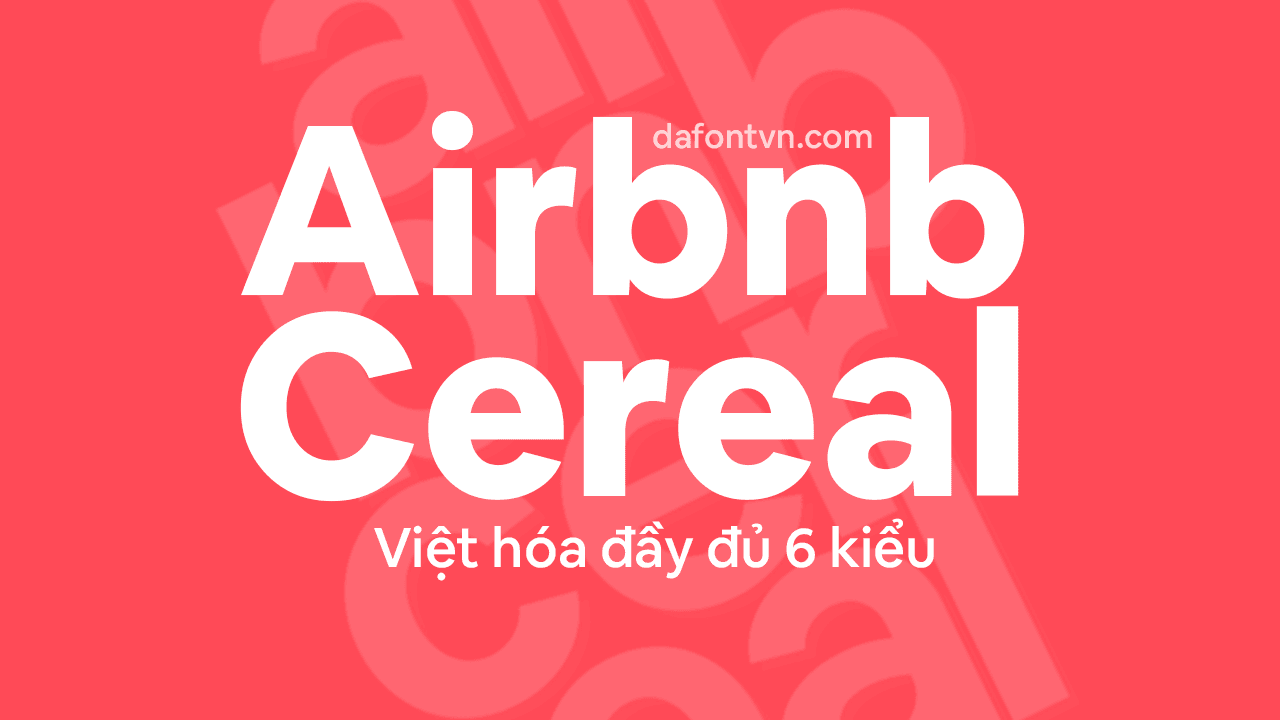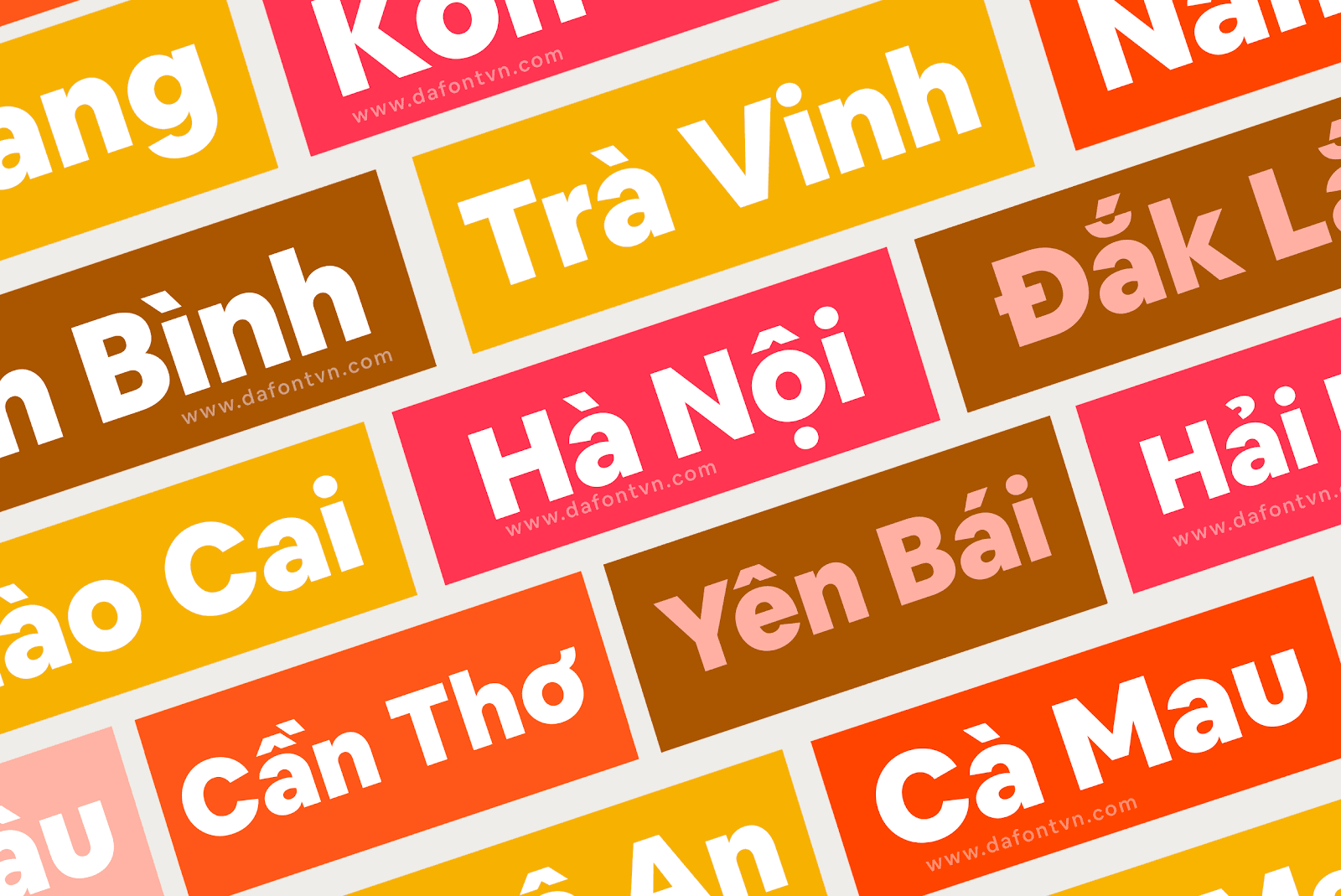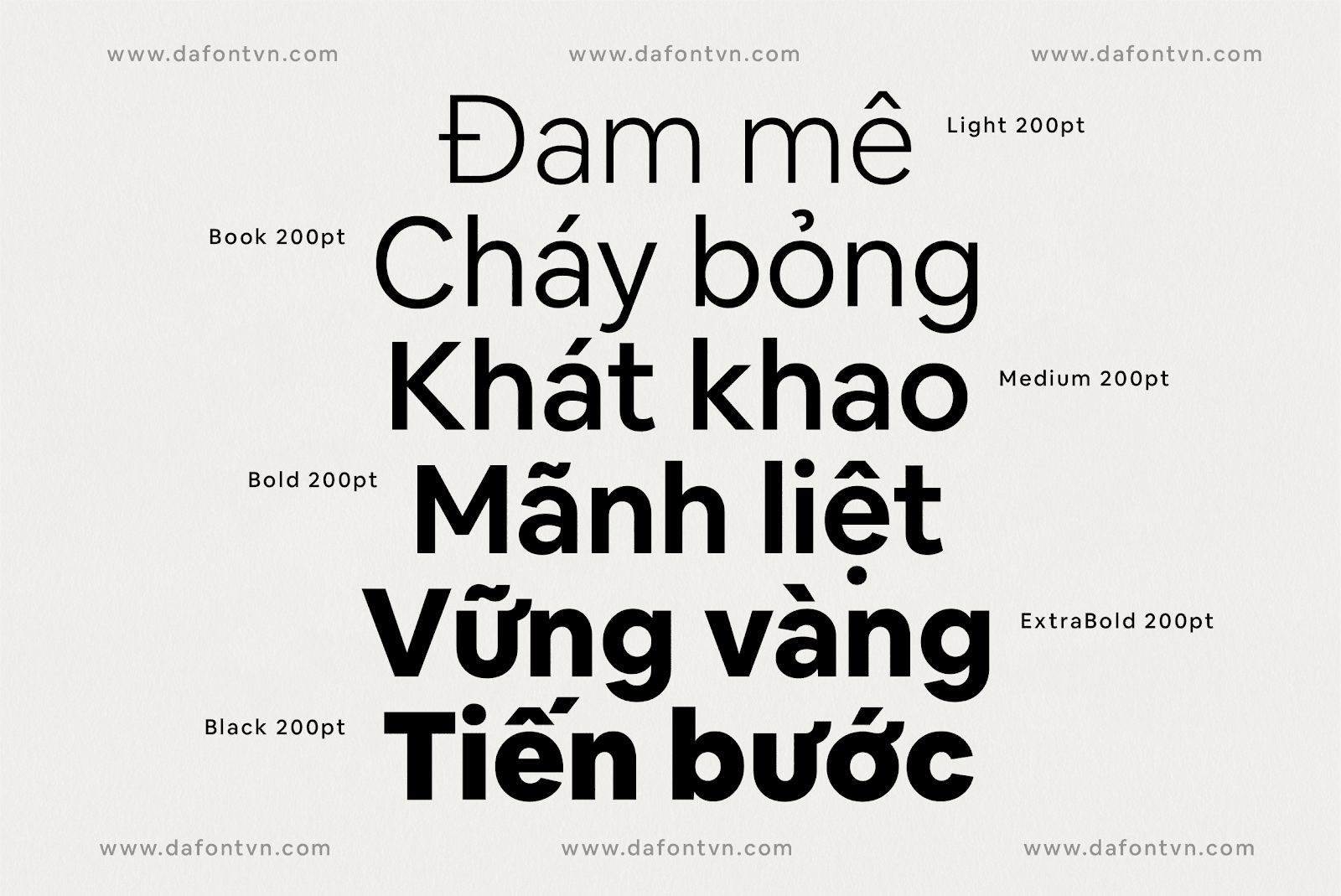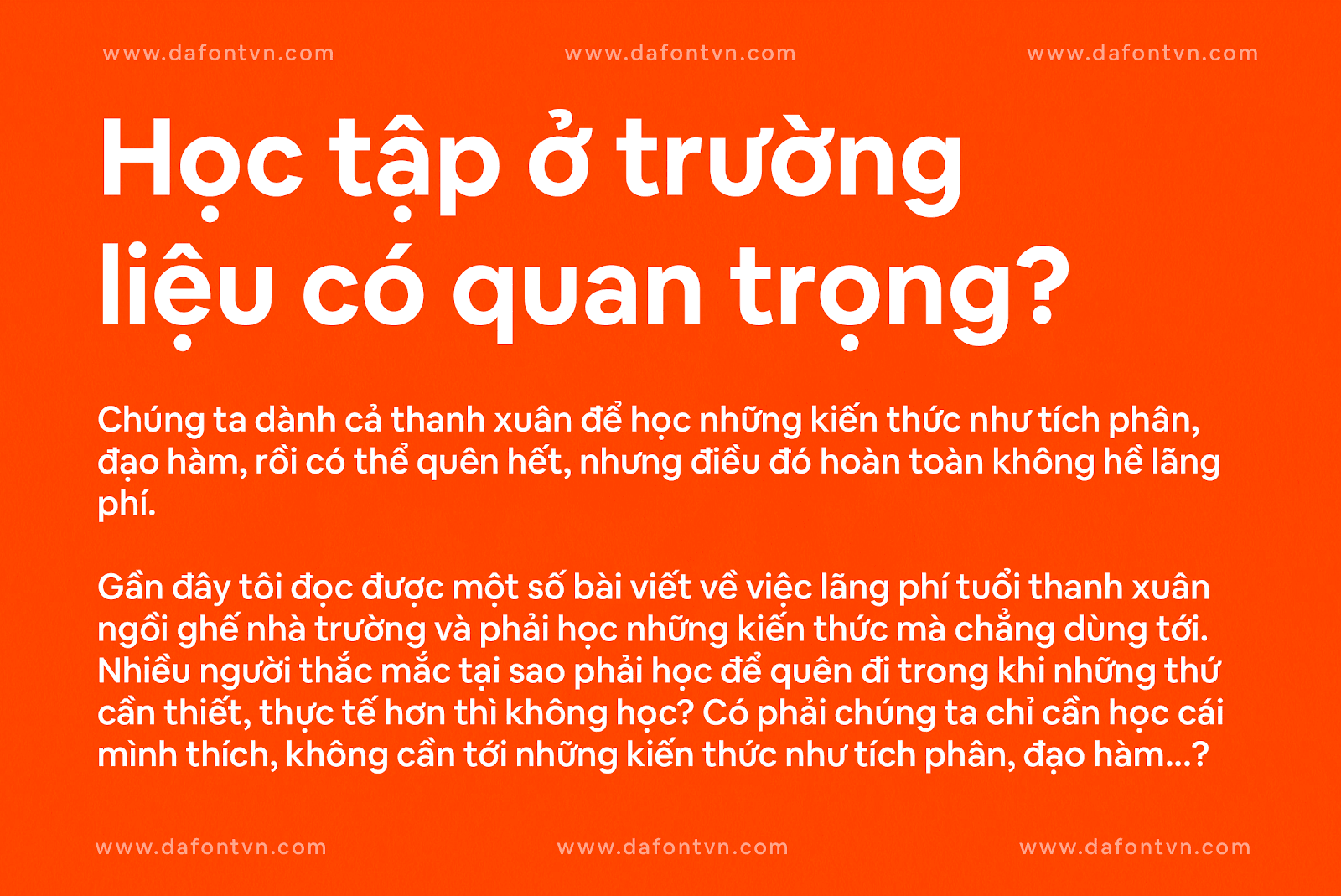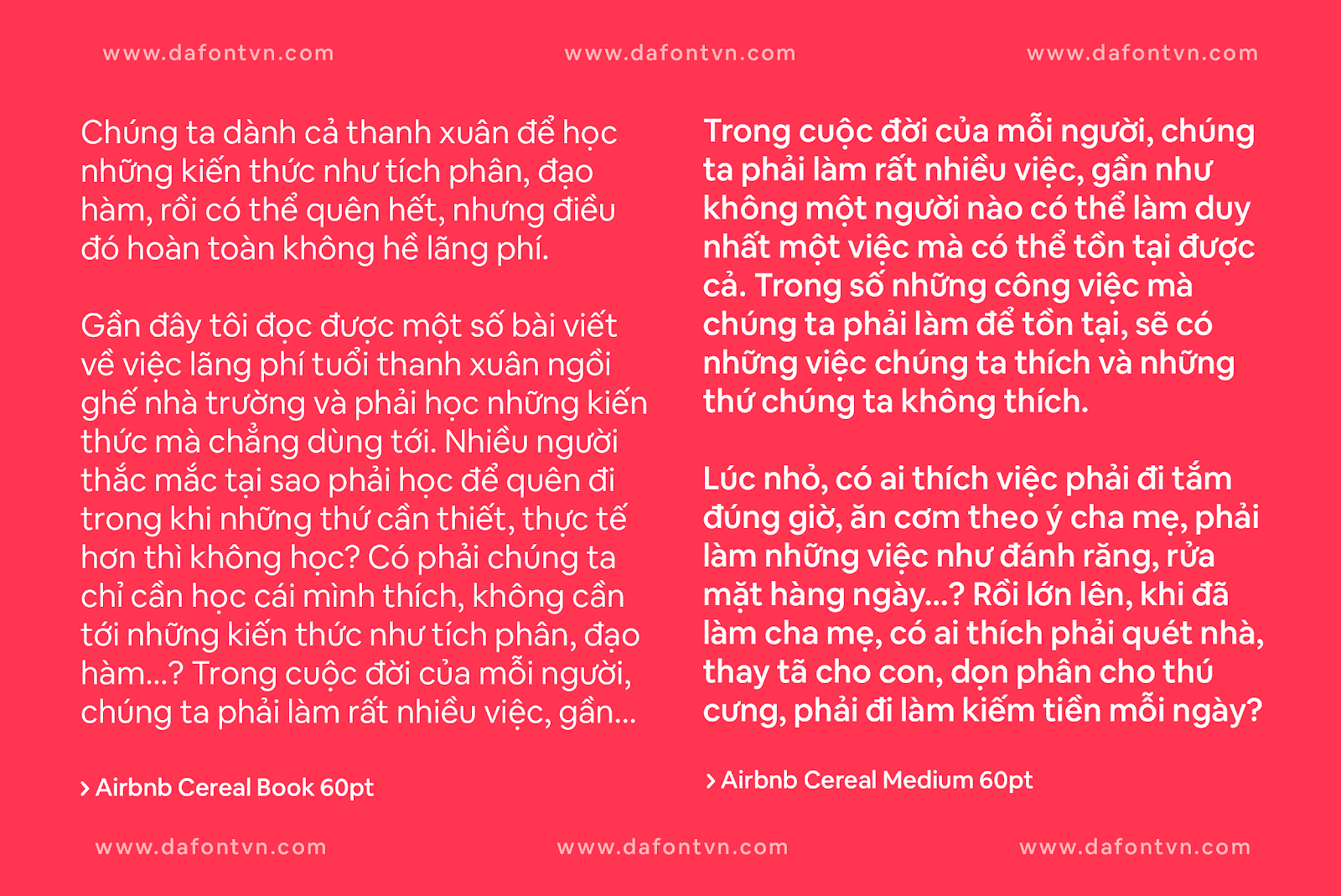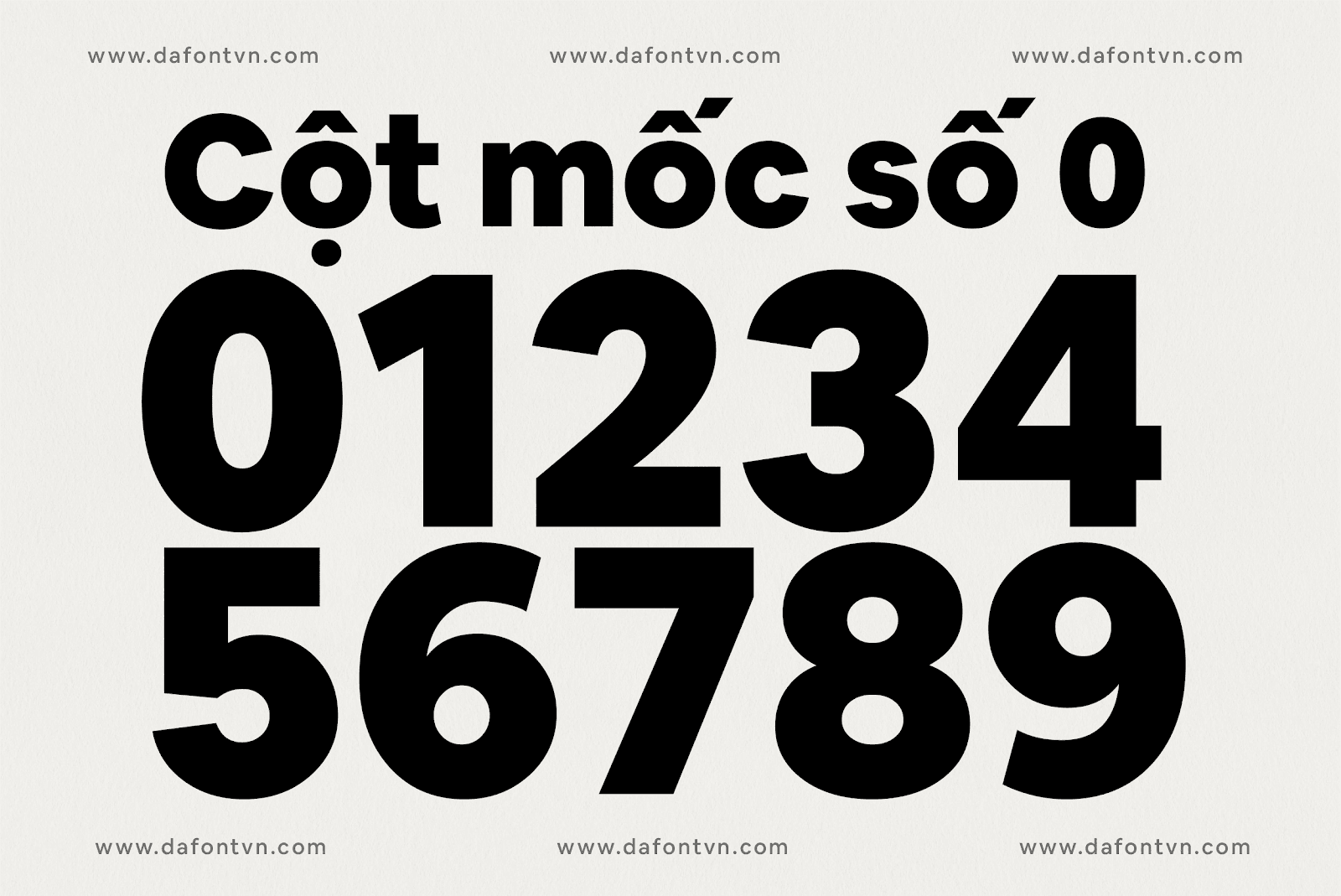
Trọn bộ font Airbnb Cereal Việt hóa (6 font)
Airbnb Cereal là kiểu font chữ được thiết kế dành riêng cho Airbnb Design một nhóm đa ngành bao gồm các nhà thiết kế, sản xuất, nhà làm phim, kiến trúc… Đây là bộ font ra mắt năm 2018 mang đến sự mới mẻ cho thương hiệu của mình, đáp ứng các tiêu chuẩn về mức độ dễ đọc và được sử dụng cả trên màn hình và ngoài màn hình.
Là một kiểu chữ sans serif hình học, bộ phông này được thiết kế với tổng thể vòng cung tạo cảm giác thân thiện và dễ tiếp cận. Từ trải nghiệm đọc chính xác ở các trọng lượng nhẹ (lighter weight) đến sự nổi bật ấn tượng ở các trọng lượng nặng (heavier weight).
Airbnb Cereal không chỉ đẹp mắt mà còn rất ấn tượng ở mọi kiểu chữ. Khả năng đọc có thể bị ảnh hưởng khi các chữ cái dễ dàng bị nhầm lẫn với nhau – đặc biệt là ở kích thước nhỏ. Vì vậy bộ phông chữ được thiết kế để mang lại trải nghiệm đọc tốt nhất ở mọi kiểu chữ khác nhau.